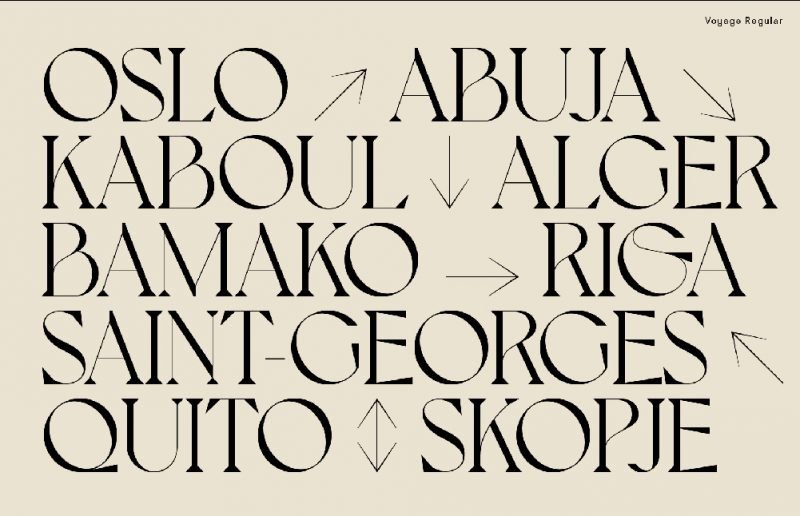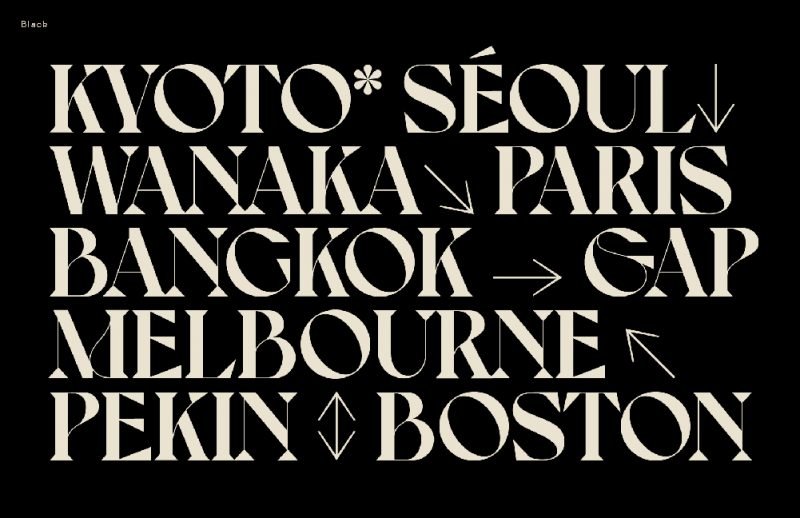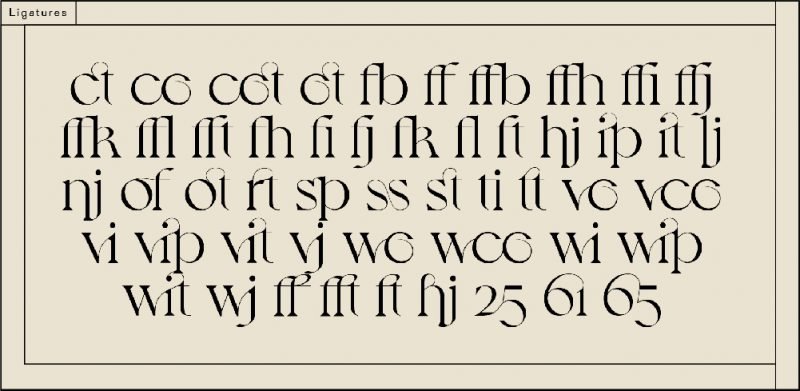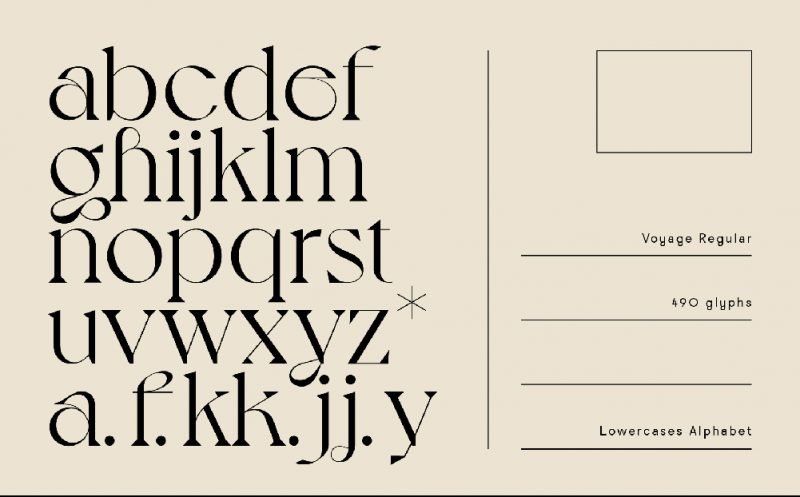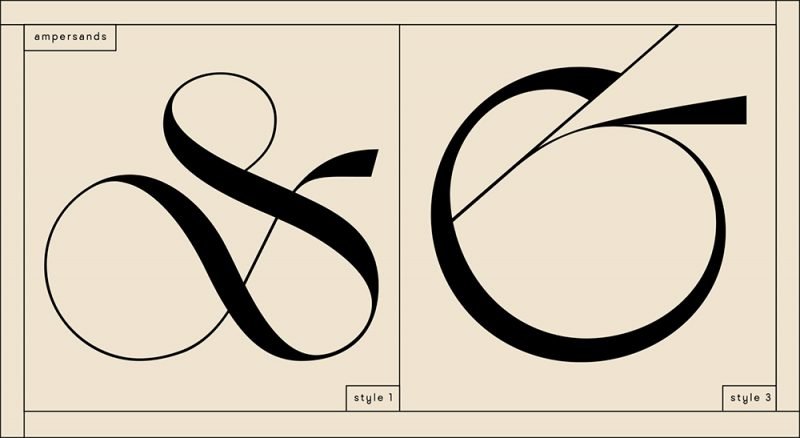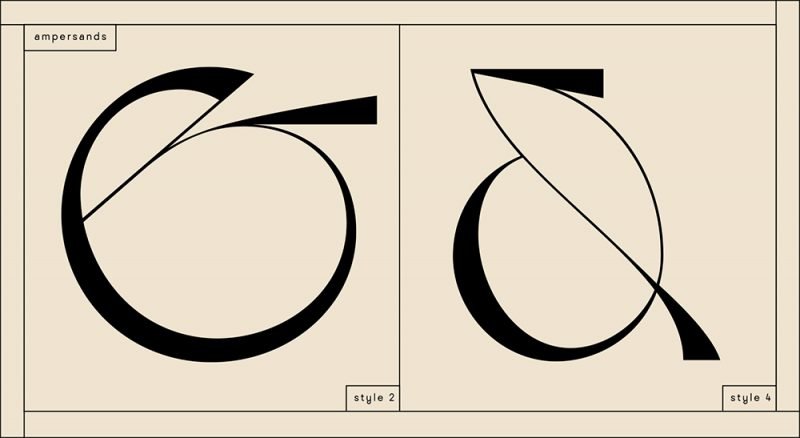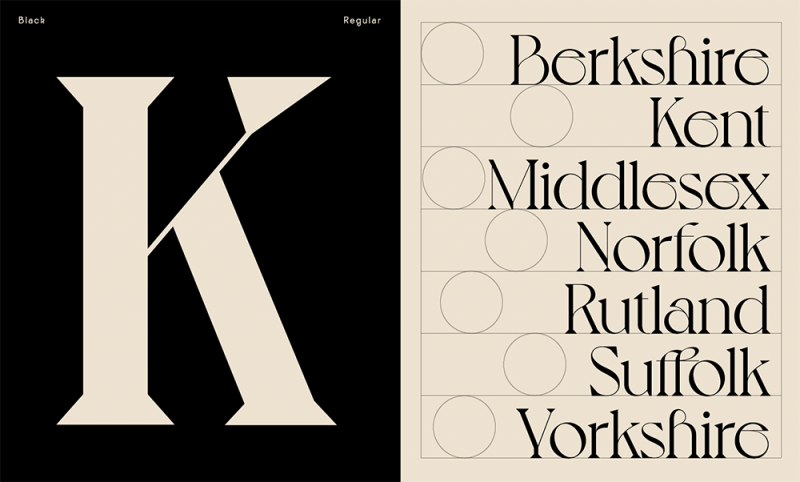
Quién es Jérémy Schneider y por qué nos gusta tanto su nueva tipografía
«Romántica y sinuosa, tal y como debe ser un viaje ¡Bon Voyage!«
Encontrar la tipografía correcta es probablemente la parte más importante de todo proceso de trabajo. Aunque actualmente Internet nos da la posibilidad de ver y acceder a millones de opciones, aspectos como la calidad, la variedad de pesos y estilos o simplemente la originalidad, hacen de esta particular tarea un suplicio en ocasiones. En este artículo presentamos una tipografía que reúne varios, sino todos, los requisitos indispensables para comenzar tu proyecto con el pie derecho.
Jérémy Schneider, la otra mitad de Violaine & Jérémy, aquel delicioso estudio parisino especializado en Gráfica y Comunicación, acaba de presentar su último proyecto tipográfico. Se trata de Voyage, una fuente para medios digitales que con sus trazos orgánicos y sus acertados remates, nos da un respiro del omnipresente flat design y la invasión de los tipos de palo seco.
Aunque esta nueva propuesta del creativo francés, pensada para titulares o como mucho para entradillas cortas, solo consta de dos pesos (Regular y Bold); sus 55 ligaduras estilísticas y 26 variantes —desarrolladas bajo protocolo OpenType—, ofrecen un margen de maniobra bastante amplio.
La combinación de trazos fuertes y finos en cada uno de los tipos, acentúa el contraste del conjunto sin entorpecer la lectura. «Voyage es romántica y sinuosa, tal y como debe ser un viaje ¡Bon Voyage!«, comenta Jérémy Schneider sobre su creación comercializada actualmente por Vj-Type.